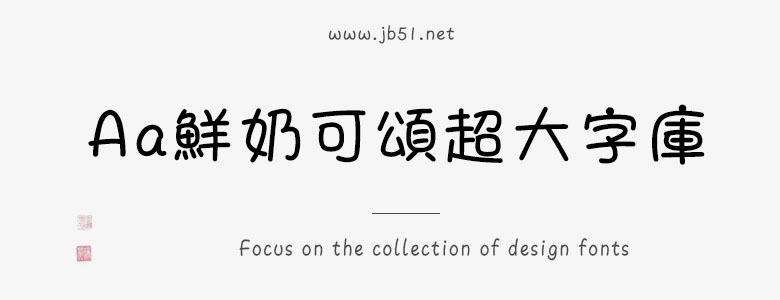
Aa鮮奶可頌超大字庫(kù)是Aa字庫(kù)推出的藝術(shù)字體,字體筆觸適中,字形圓潤(rùn) ,具有很好的視覺(jué)感,適合應(yīng)用于藝術(shù)設(shè)計(jì)、平面宣傳設(shè)計(jì)、網(wǎng)頁(yè)設(shè)計(jì),書法字帖等領(lǐng)域,歡迎需要的朋友下載使用。